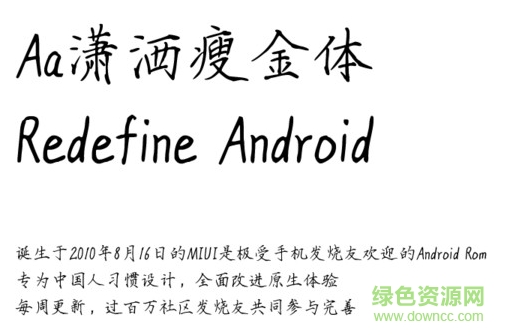
瀟灑瘦金體是一款很有魏晉豐富的瘦金字體,行筆流暢不失承轉(zhuǎn)合之美,字體灑脫延續(xù)魏晉飄逸之風,喜歡的朋友就來綠色資源網(wǎng)收藏吧!
瘦金體運筆靈動快捷,筆跡瘦勁,至瘦而不失其肉,其大字尤可見風姿綽約處。因其筆畫相對瘦硬,故筆法外露,可明顯見到運轉(zhuǎn)提頓等運筆痕跡,是一種風格相當獨特的字體。
瀟灑瘦金體
瘦金體書法特色
宋徽宗的書法筆畫瘦硬,初習黃庭堅,后又學褚遂良和薛稷、薛曜兄弟,并雜糅各家,取眾人所長且獨出己意,最終創(chuàng)造出別具一格的“瘦金書”體,影響頗大。
瘦金書是一種風格相當獨特的字體。此書體以形象論,本應為“瘦筋體”。以“金”易“筋”,是對御書的尊重。這是一種非常成熟的書體,趙佶已把它的藝術個性發(fā)揮得淋漓盡致。這種瘦挺爽利、側(cè)鋒如蘭竹的書體,是需要極高的書法功力和涵養(yǎng),以及神閑氣定的心境來完成的。